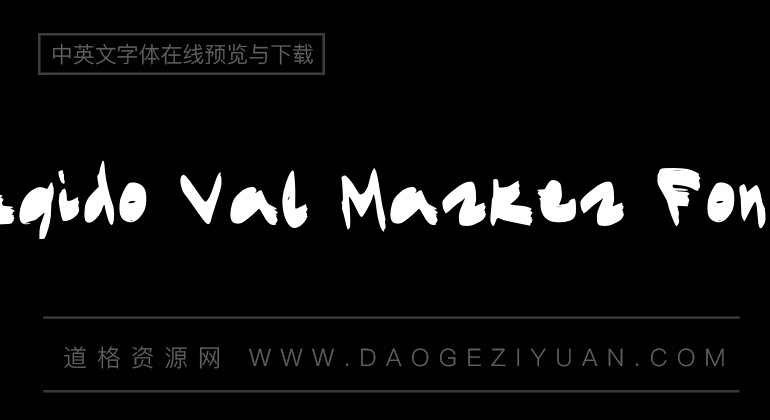
Egido Val Marker Font
Egido Val Marker Font 是一种手写风格的字体,它的特点是线条粗细不一,仿佛是手写的。该字体由设计师 Egido Valdez 创作,适用于多种设计场景,如海报、书籍封面、标志、印刷品等等。 该字体有两种风格,一种是 Egido Val Marker Font,另一种是 Egido Val Marker Font Alt。两种风格的差别在于字母的形状有所不同。这种风格的字体适合于给设计带来一种自然、粗糙的感觉,非常适合创意类的设计。 Egido Val Marker Font 字体可以从多个网站免费下载,也可以在付费字体商店购买。
Egido Val Marker Font是一款非常不错的手写艺术字体,具有很好的视觉感,适合于文化类的宣传设计、商业类品牌的广告和产品包装设计以及个性化文字排版等较多场景。